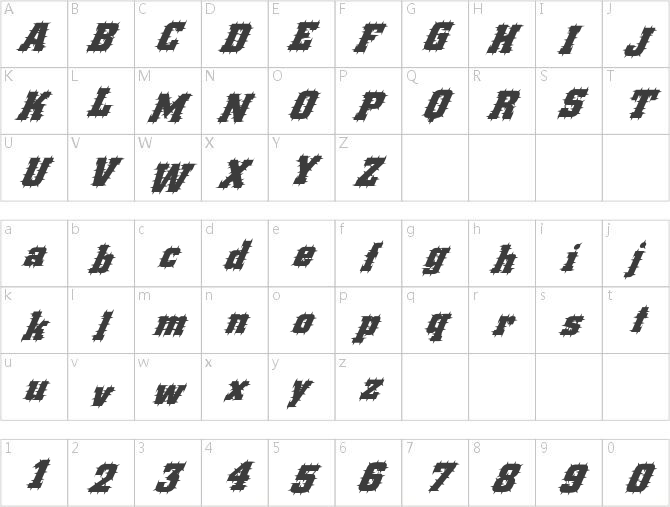
FZ BASIC 53 SPIKED ITALIC
FZ BASIC 53 SPIKED ITALIC字體字庫是一款讓人賞心悅目、百看不厭的英文字體,適合各類廣告和產(chǎn)品包裝設(shè)計應(yīng)用,字體大小0.07MB,格式為ttf字體,上傳用戶是woslxn,作者/版權(quán)方為未知